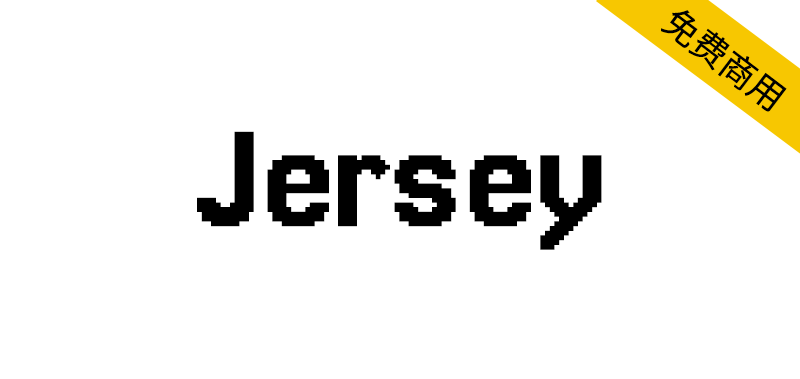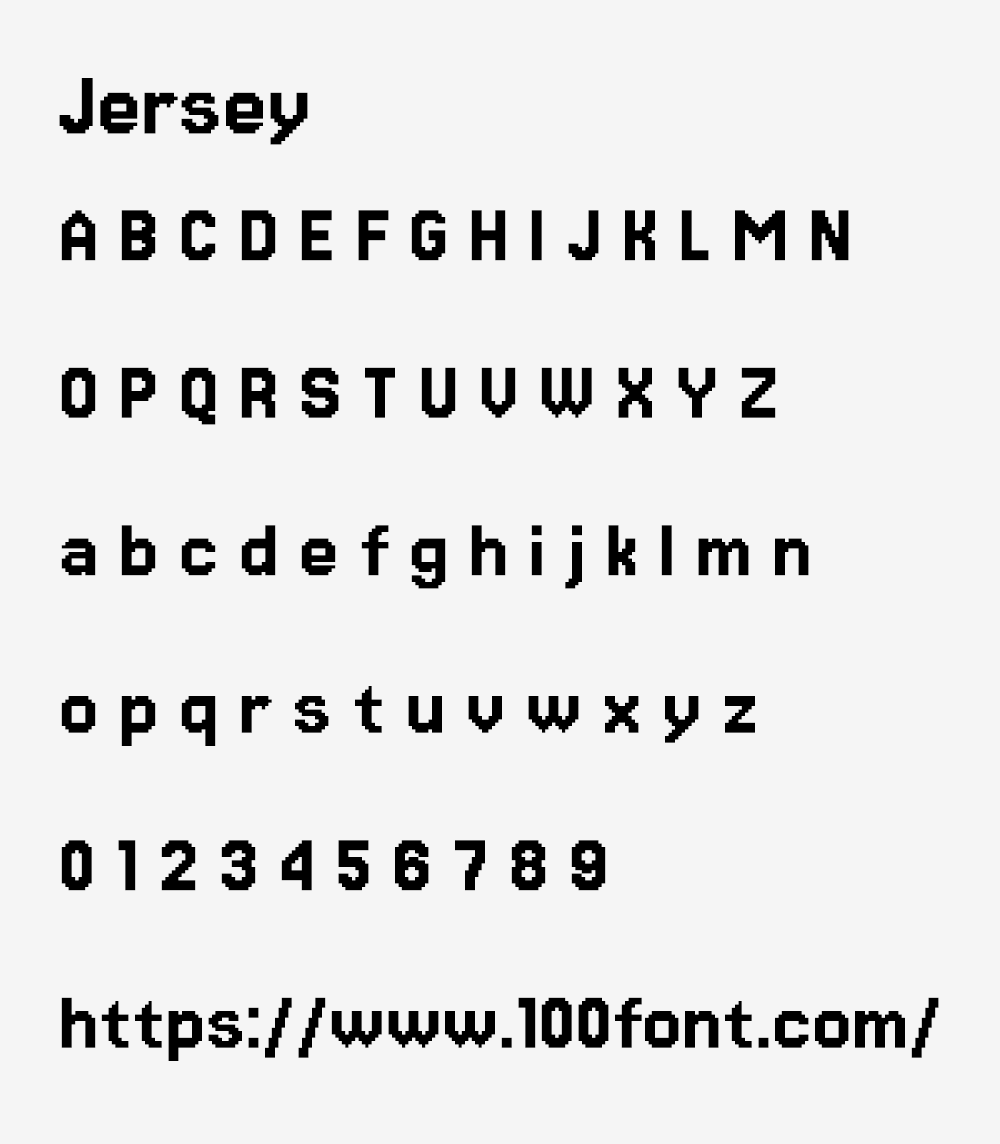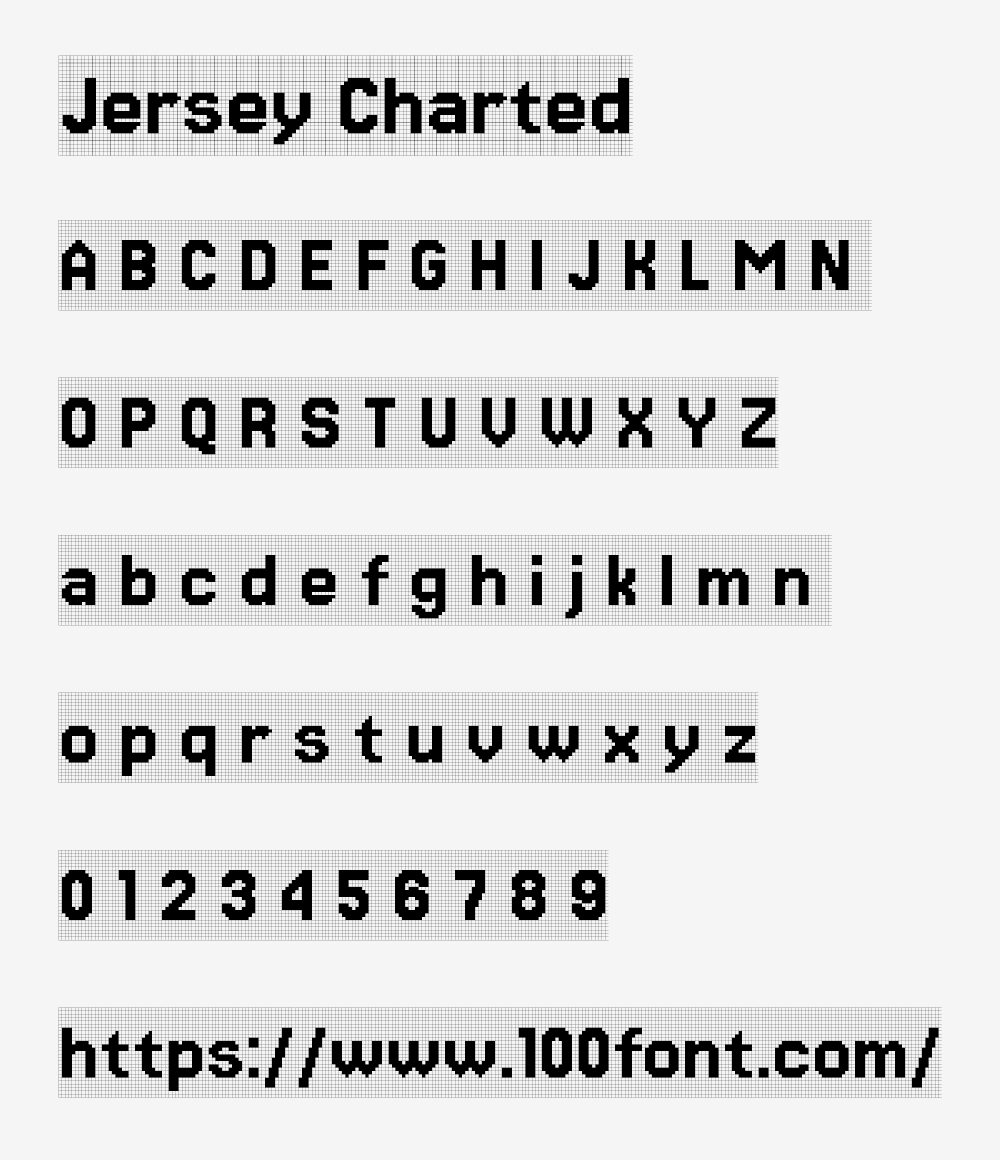
Jersey 是一款充满运动感的多用途无衬线字体,支持多种尺寸编织。Jersey是一套专为彩色编织设计的字体合集。每款字体均包含「常规版」和「图表版」,部分字体还提供多种比例尺寸,确保任何大小的编织项目都能完美适配文字。
设计理念:为编织设计字体本质上与设计像素字体相同。但实际应用中,像素大小由所用纱线的特性决定——比例取决于纱线粗细以及构成每个字母高度的像素数。本合集中,字体名称后的数字代表该字体大写字母的高度(单位:像素)。
适用场景:这些字体虽然是为机器编织而设计,但同样适用于手工编织、刺绣、珠饰、其他纺织工艺。
Jersey is a sporty, versitile sans-serif typeface, knittable at various sizes.Soft Type is a collection of typefaces designed for knitting color-work. Each typeface has a “Regular” and “Charted” version and some include multiple scales so you can fit type on your knits, no matter the project's size.
Designing typefaces for knitting is essentially the same as designing pixel type. However, in practice, the pixel size is determined by the properties of the yarn in use. Scale is determined by the weight of the yarn as well as the number of pixels that make up the height of each letter. In this collection, the number following the name of the typeface indicates the height of the capital letters for that typeface.
These typefaces were designed with machine knitting in mind, but could be used for hand knitting, needlework, bedazzling, or many other textile crafts.